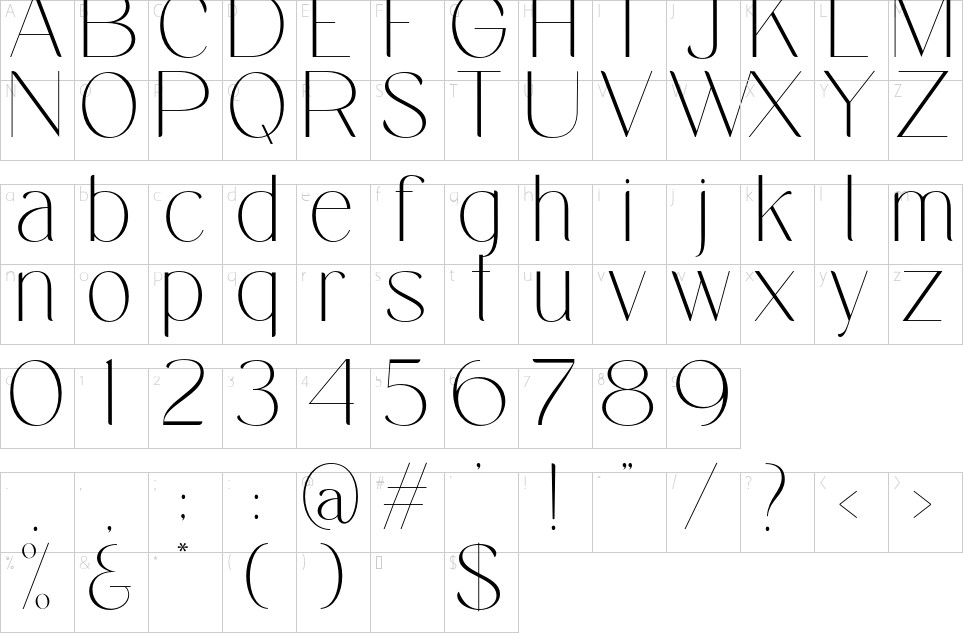
A fonte Midland Luxury é uma escolha perfeita para quem busca uma estética sofisticada e elegante para seus projetos digitais. Desenvolvida pela Areatype, a Midland Luxury oferece linhas elegantes e detalhes atraentes, que adicionam um toque de luxo a qualquer design. Esta fonte foi projetada para criar textos profissionais e sofisticados, ideal para criar materiais de marketing, design gráfico ou qualquer aplicação que precise de uma aparência de luxo. Conhecida por seus detalhes cuidadosamente criados, a Midland Luxury é uma escolha sólida para qualquer designer que busca qualidade e estilo em sua fonte escolhida. Recomendada para aqueles que buscam uma fonte de alto nível para um projeto, a Midland Luxury é uma fonte gratuita de alto nível, disponível tanto para Windows quanto para Mac.